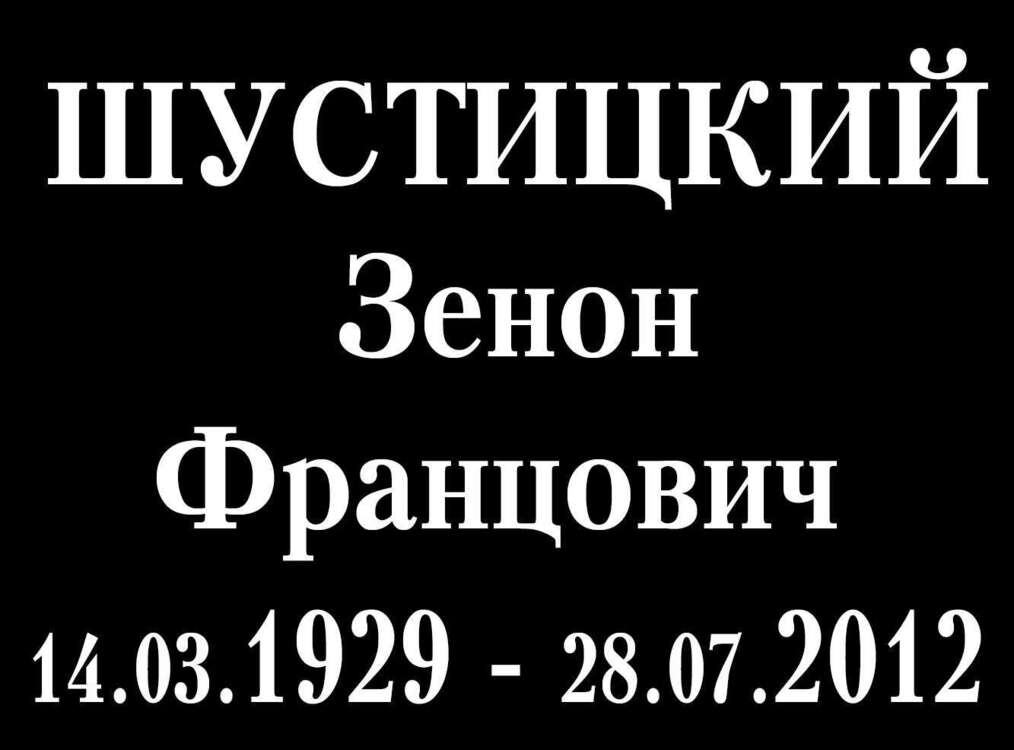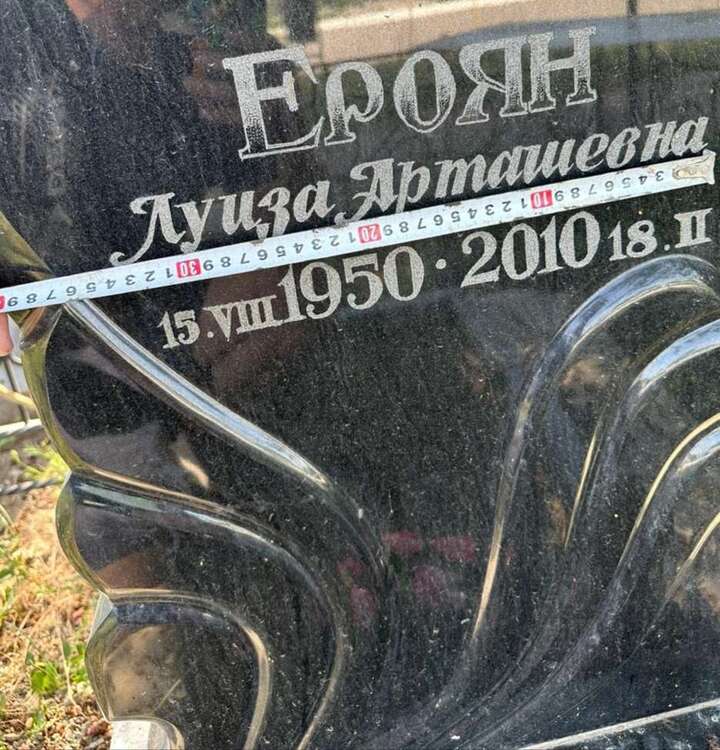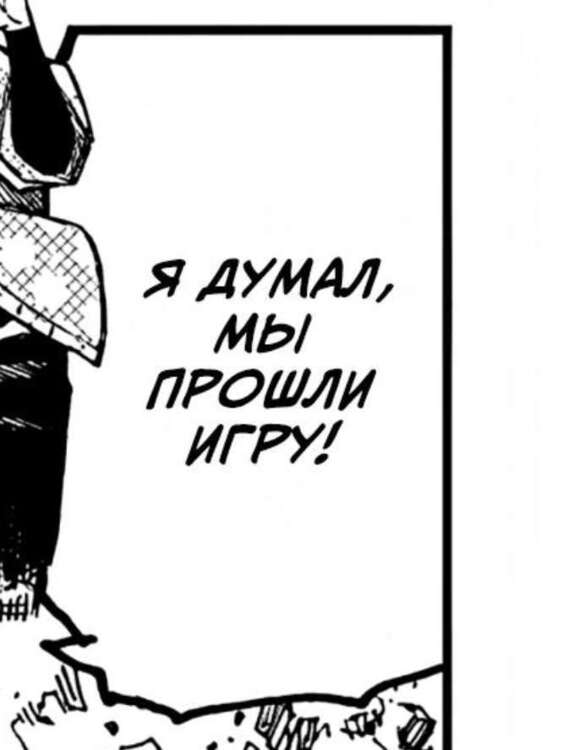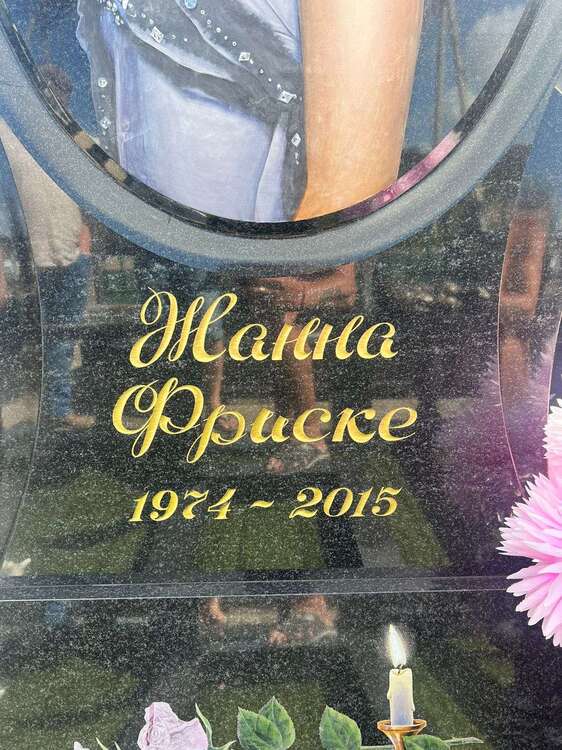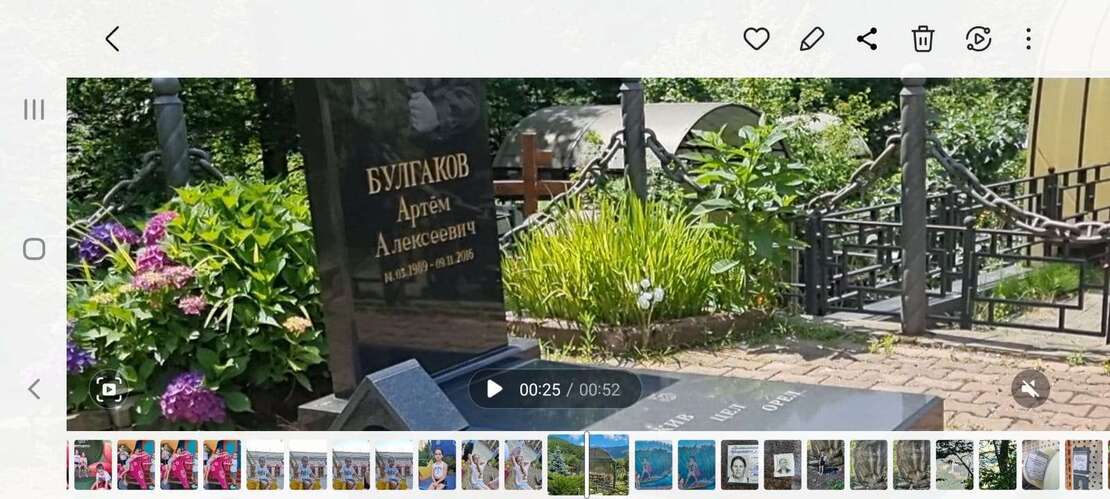
Помогите найти шрифт!
Здравствуйте, не подскажите что за шрифт
@Melnichsd Очередное творчество "ручника".
да видно рука ручного мастера, ищу теперь что-то похожее
@Melnichsd Фамилию сделать можно через градиент. А Имя Отчество - шрифт можно покопать, но точь-в точь естественно не найти.
Здравствуйте, подскажите что за шрифт
Всех приветствую, подскажите максимально похожий шрифт пожалуйста, по буквам Refrigerator вроде похож, а вот цифры не могу подобрать.
Присмотрись к шрифту MachineC в целом, возможно устроит целиком и полностью:hmm:
Добрый день, не подскажите что за шрифт?
@Melnichsd У меня большая коллекция шрифтов. Такого не нашла. Видимо "ручник" фантазировал))
@Melnichsd тогда, посмотрю чуть позже еще. Чем смогу, помогу))
И снова просьба найти шрифт
@угрюмый Monotype Corsiva
Доброго здоровья всем форумчанам... господа нид хэлп.... что это за чудный шрифт, качество фото -скрин с видео....
Times New Roman
похож?
@ПавелСерп Lucida Bright   Посмотри этот.....
Ребята, может у кого есть примерный, похожий ( теперь я не могу найти) шрифт.